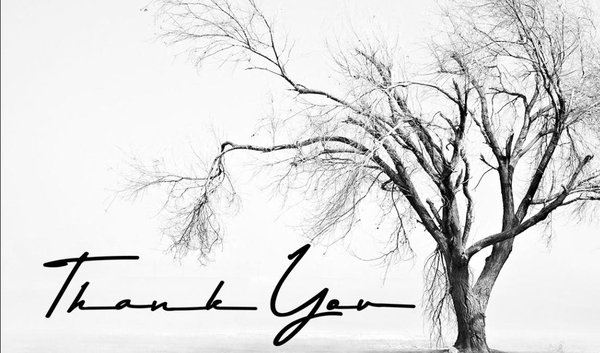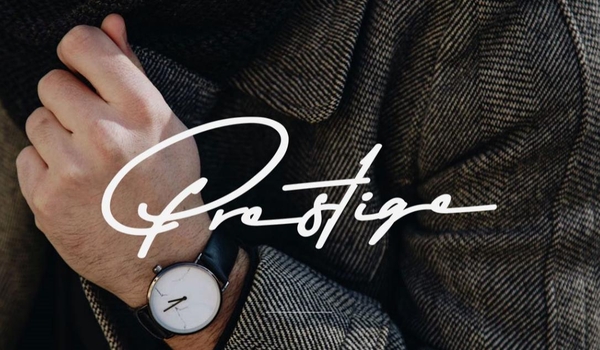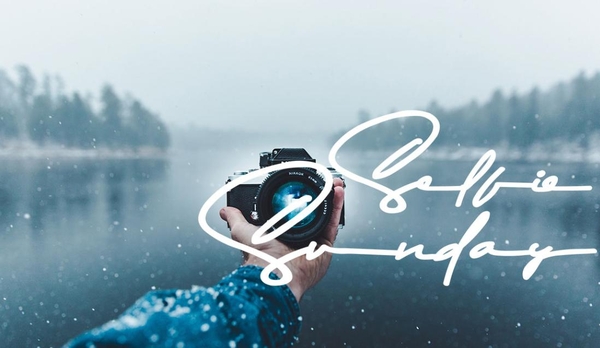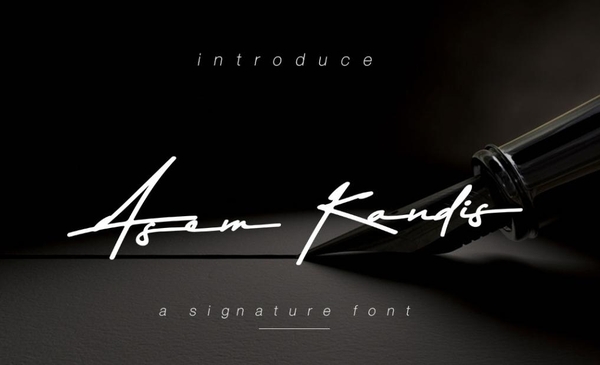
Tìm hiểu đôi chút về Font chữ ký Asem Kandis Signature
Font chữ Asem Kandis được thiết kế và chia sẻ bởi Lemoncraft . Font chữ Asem Kandis là một font chữ ký Script hiện đại thanh lịch, hỗ trợ một bộ các ký tự Latinh với chữ ấn tượng và sành điệu. Font chữ này chứa một tập hợp đầy đủ các chữ cái viết thường và chữ in hoa, dấu chấm câu, số và cả một bộ chữ ghép thời trang. Asem Kandis Font Script là một phông chữ viết tay chất lượng cao , có thể nhúng bất kỳ dự án nào với các rung động Uy tín. Chữ ký, lời mời đám cưới, Logo thanh lịch, đồ gốm và các dự án ấn tượng khác.